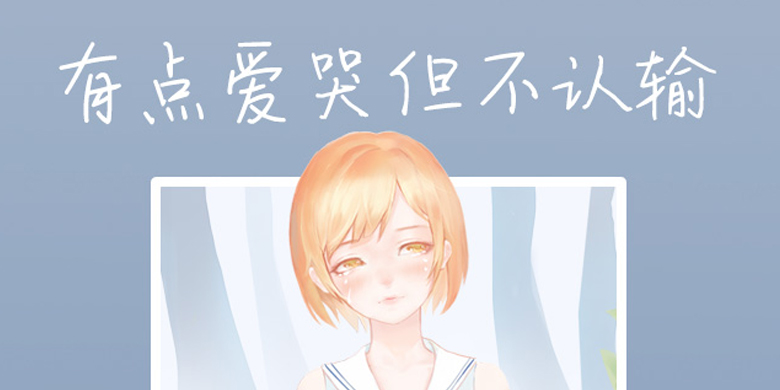
方正手迹-有点爱哭但不认输
方正手迹-有点爱哭但不认输,这款字体结构工整、笔画清晰,兼顾美观与易读性,适用于标题、正文、海报、包装、LOGO 等多种场景。字形优雅稳定,风格百搭耐看,适配日常排版与创意设计,让文字呈现更舒适、更具质感。方正手迹-有点爱哭但不认输一笔一画,皆是细节,以均衡的比例、流畅的线条打造舒适视觉体验,字形端正大气,风格简约现代。无论是商业设计、品牌宣传还是日常排版,都能轻松驾驭,让文字更有格调与力量。方正手迹-有点爱哭但不认输字体下载。
字体品牌: 方正手迹 设计师:俞亦婷 字体分类:常规书写·硬笔 字体属性:精品字 字符集:简繁扩展(GBK) 发布时间: 2020
该字部件设计上运用较多的圆角,使得该字具有良好的亲和力。字形上给人感觉洒脱飘逸,排版有错落有致的阅读体验。适用于文艺类的书刊、品牌广告和产品包装设计,以及社交网络的个性化用字。